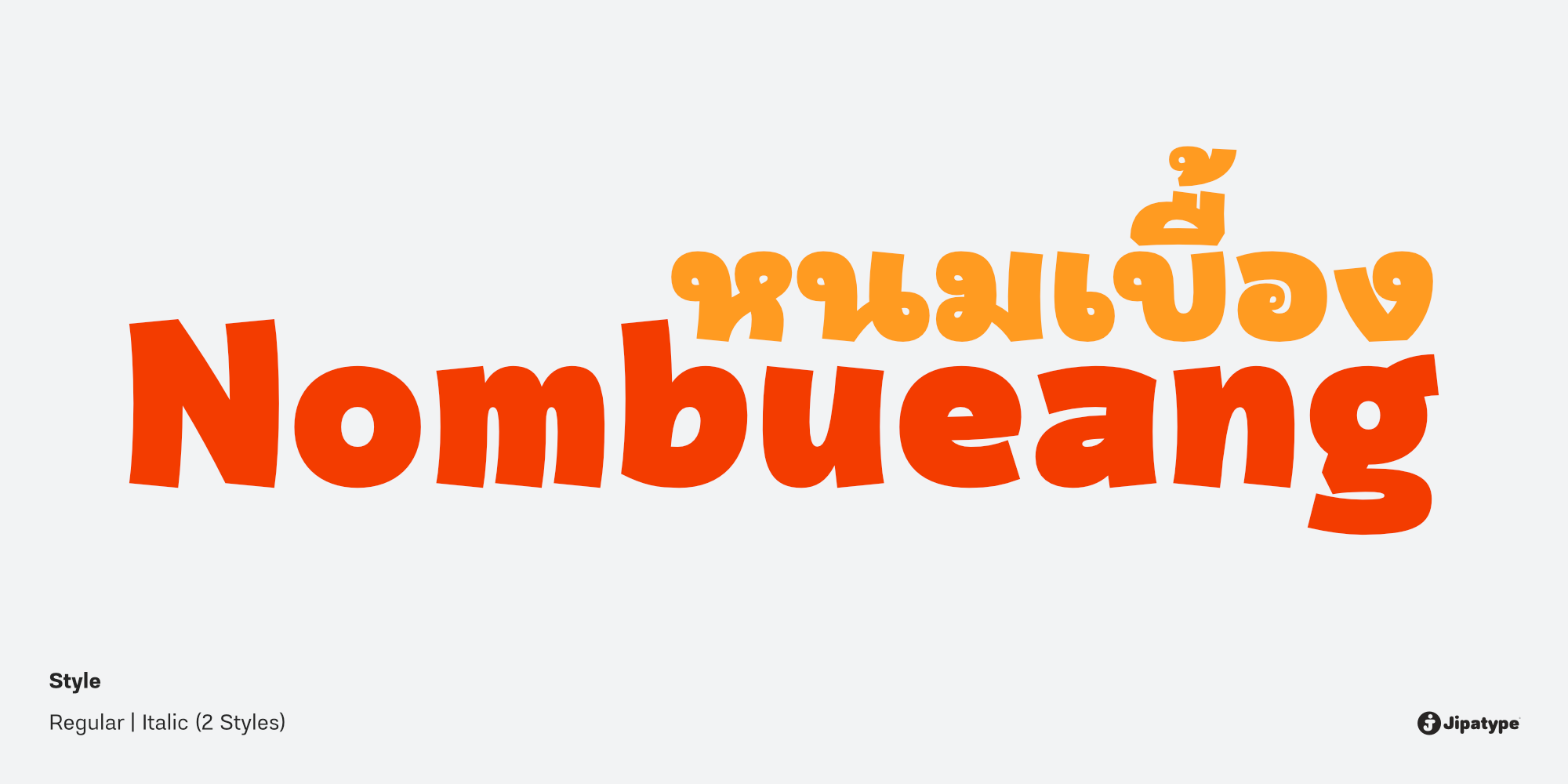
หนมเบื้อง | Nombueang
ชื่อฟอนต์ : หนมเบื้อง | Nombueang
หนมเบื้อง เป็นแบบอักษรพาดหัวแบบไม่เป็นทางการ มีรูปลักษณ์ที่ตัวหนาและตัวอักษรไทยเป็นแบบมีหัว ให้ความรู้สึกสนุกสนาน เป็นมิตร และอบอุ่น เหมาะสำหรับการนำไปใช้พาดหัวบนสื่อต่างๆ หรือความที่ต้องการเน้นความสำคัญเป็นพิเศษ เช่น โปสเตอร์ แพคเกจจิ้ง และอื่นๆ อีกมากมาย
Nombueang is an informal headline typeface with a bold appearance and loop-headed Thai letters, giving it a fun, friendly, and warm feeling. It is suitable for use in various media and is especially effective in emphasizing special importance, such as in posters, packaging, and more.
Creator : อานุภาพ ใจชำนาญ (Anupap Jaichumnan)